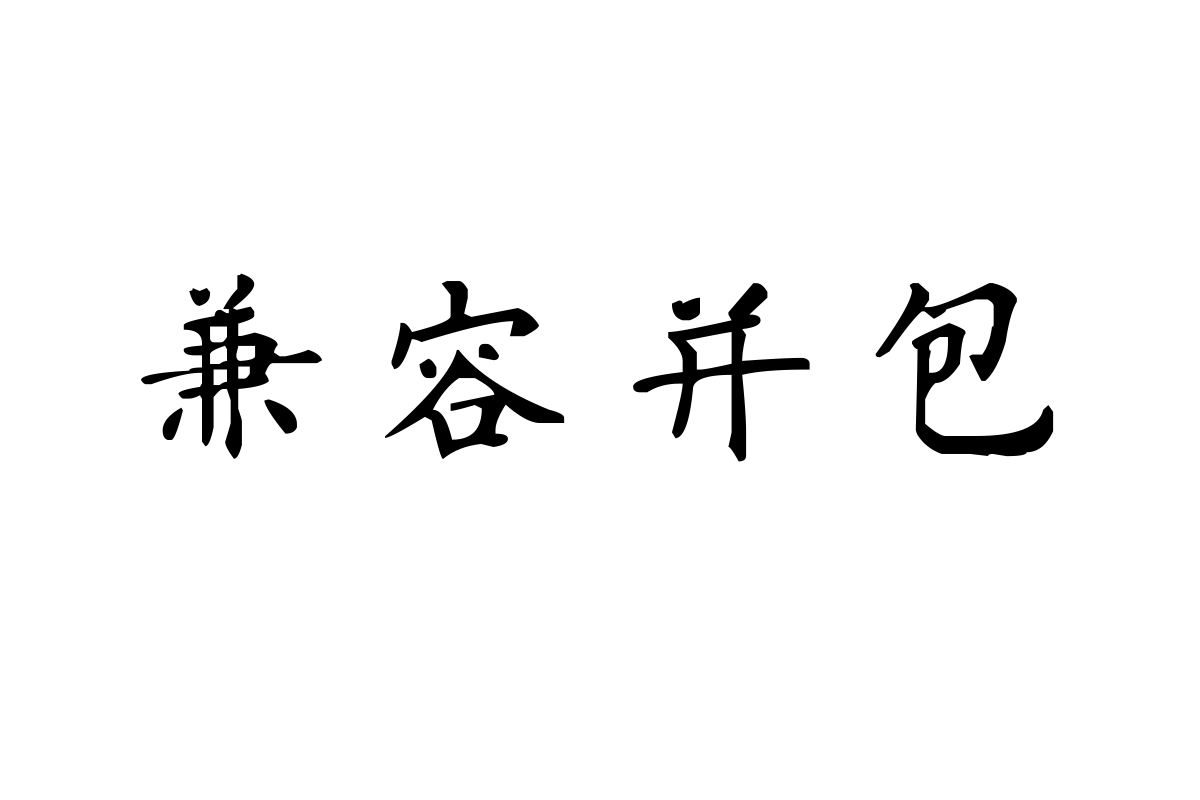
汉标丁祥红毛笔楷书是一款具有独特魅力的书法字体,其特点如下:
1. 字形结构严谨:该字体在字形结构上遵循了传统的楷书规范,笔画清晰,结构严谨,给人以庄重、大方的感觉。
2. 笔画流畅:汉标丁祥红毛笔楷书的笔画流畅自然,线条圆润饱满,给人一种优雅、流畅的视觉享受。
3. 笔锋有力:该字体的笔锋有力,表现出书法家扎实的功底和对书法艺术的热爱。
4. 风格独特:汉标丁祥红毛笔楷书在传统楷书的基础上进行了创新,形成了独特的风格,既有传统的韵味,又不失现代的审美。
5. 适用范围广泛:该字体适用于各种场合的书写,如书法作品、宣传海报、广告设计等,具有较高的实用价值。
总之,汉标丁祥红毛笔楷书是一款具有独特魅力的书法字体,其特点在于字形结构严谨、笔画流畅、笔锋有力、风格独特,适用于多种场合的书写。